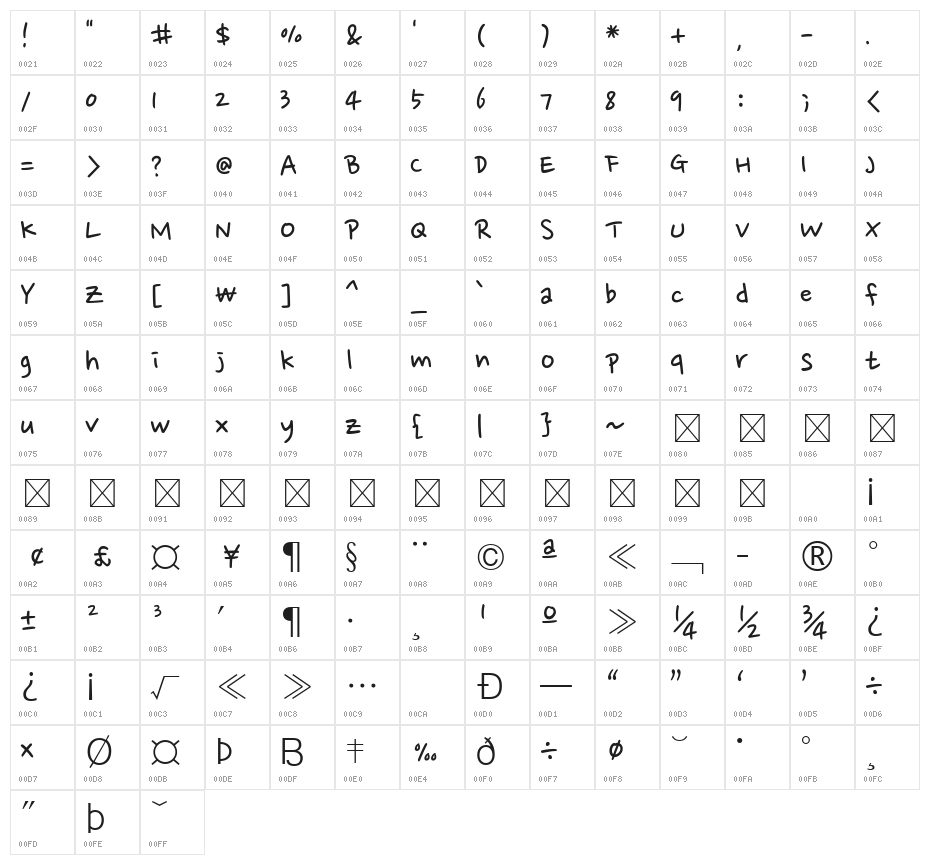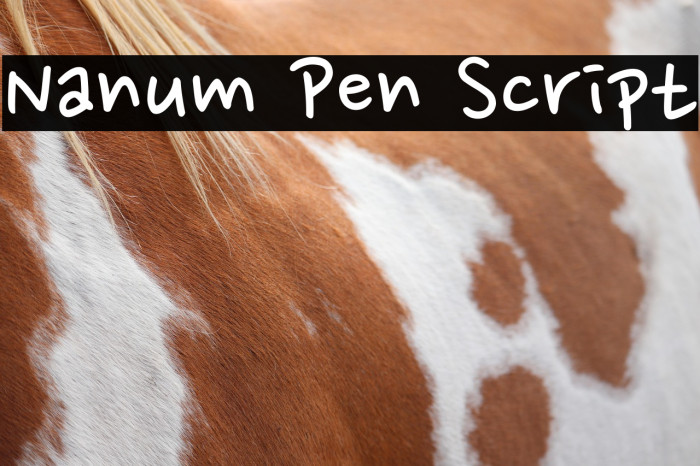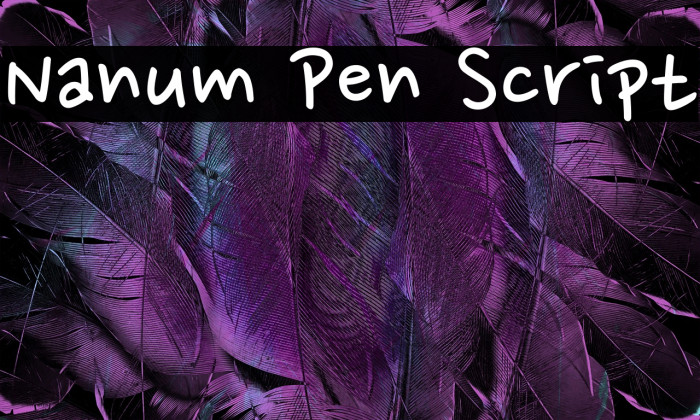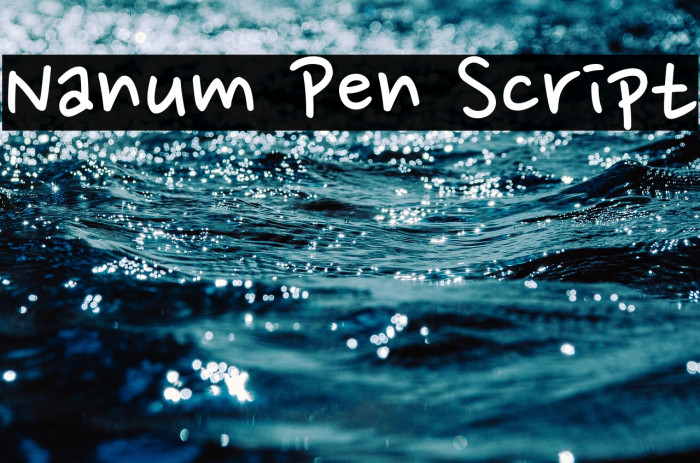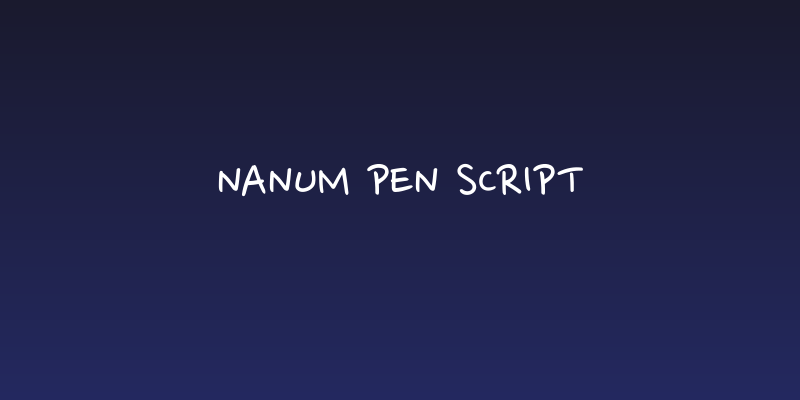
Nanum Pen Script Font
| Stile generale | Casual, Friendly |
| Caso d'uso | Invitations, Personal notes, Creative branding |
| Progetti proposti | Ideal for personal notes, invitations, greeting cards, and creative branding projects. |